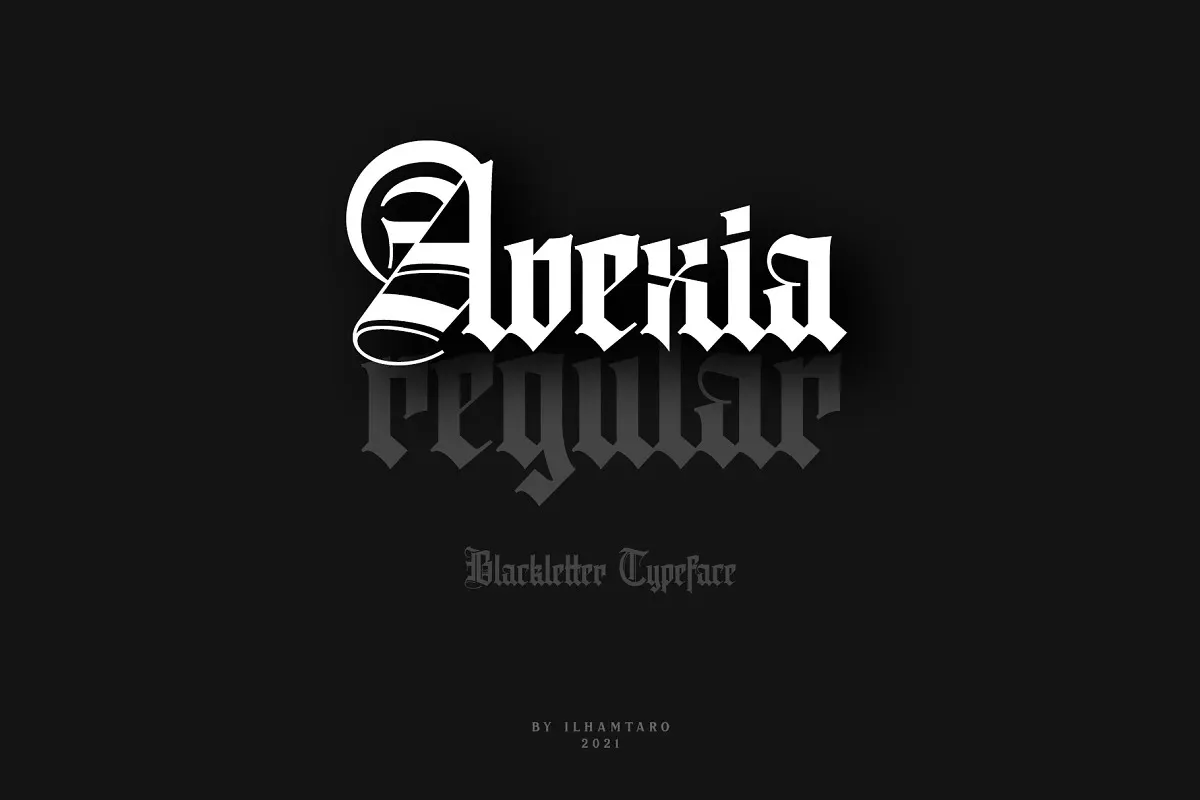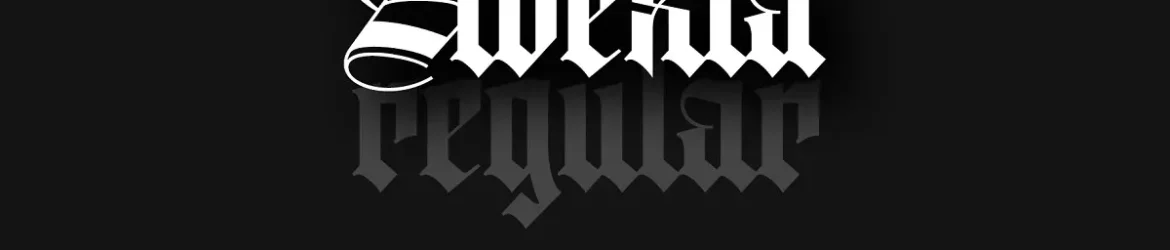
Avexia Font – Download Grátis
Avexia Font é uma nova face do tipo blackletter que traz elementos modernos e góticos. Embora seja inspirado no estilo gótico clássico, foi projetada para se encaixar mais facilmente em um design contemporâneo e jovem. Esta fonte modernizou a simplicidade tradicional dos typológos blackletter, tornando-a perfeitamente adequada para trabalhos com temas gothen, vintage, rock ou mesmo embalagens de bebidas alcoolicas. Seja para projetos que valorizam o estilo gótico ou vintage, Avexia Font é uma escolha agradável e versátil no seu catálogo de fontes. Ideal para quem busca um touch mais moderno neste tipo específico de letras serifadas, Avexia é sua fonte perfeita.